From metal to digital從金屬到數字的演變
從古騰堡時代到工業革命,歐洲印刷技術基本保持不變,主要依靠手工製作金屬活字和手動印刷。19世紀印刷業實現機械化,隨後發展加速 - 20世紀見證了從熱鉛字到照相排版再到數字時代的轉變,為字型設計帶來更多可能。
Rise of the sans serif 無襯線字型的崛起
無襯線字型雖在19世紀初出現,但20世紀才真正流行。從笨重的全大寫字母發展為重要字型型別,它逐漸擺脫了襯線字型的影響。設計師追求統一風格,降低字形對比度,斜體設計也改為直接傾斜而非模仿手寫。1957年的Helvetica是典型案例,它源自1898年的Akzidenz-Grotesk,隨著軟體和作業系統的普及成為最常用的數字字型之一。
簡化字母的趨勢體現在1927年Paul Renner設計的Futura幾何無襯線字型中,並在德國標準化學會的DIN 1451字型中達到巔峰。DIN字型創造了現代標準字母表,將無襯線風格標準化,廣泛用於德國道路標識和車牌,影響了眾多現代無襯線字型。
Light, digital, and postmodern type 光與數字時代的字型設計
20世紀初期金屬活字技術仍沿用15世紀方法,但逐漸發展出機械化鑄字。1890年代發明的照相排版技術到1960年代才普及,用底片字母負像代替立體字模,提高了效率。照相排版機使用感光材料印製字母,加快了排版速度且無需儲存金屬字模,但很快被數字技術取代。
1980年代中期,個人電腦讓排版設計不再侷限於專業技師,任何人都能嘗試字型設計。早期數字設計師從低解析度螢幕獲得靈感,開創新方法,同時思考如何用新技術重現傳統字型。工程師解決技術問題,設計師關注成品質量。
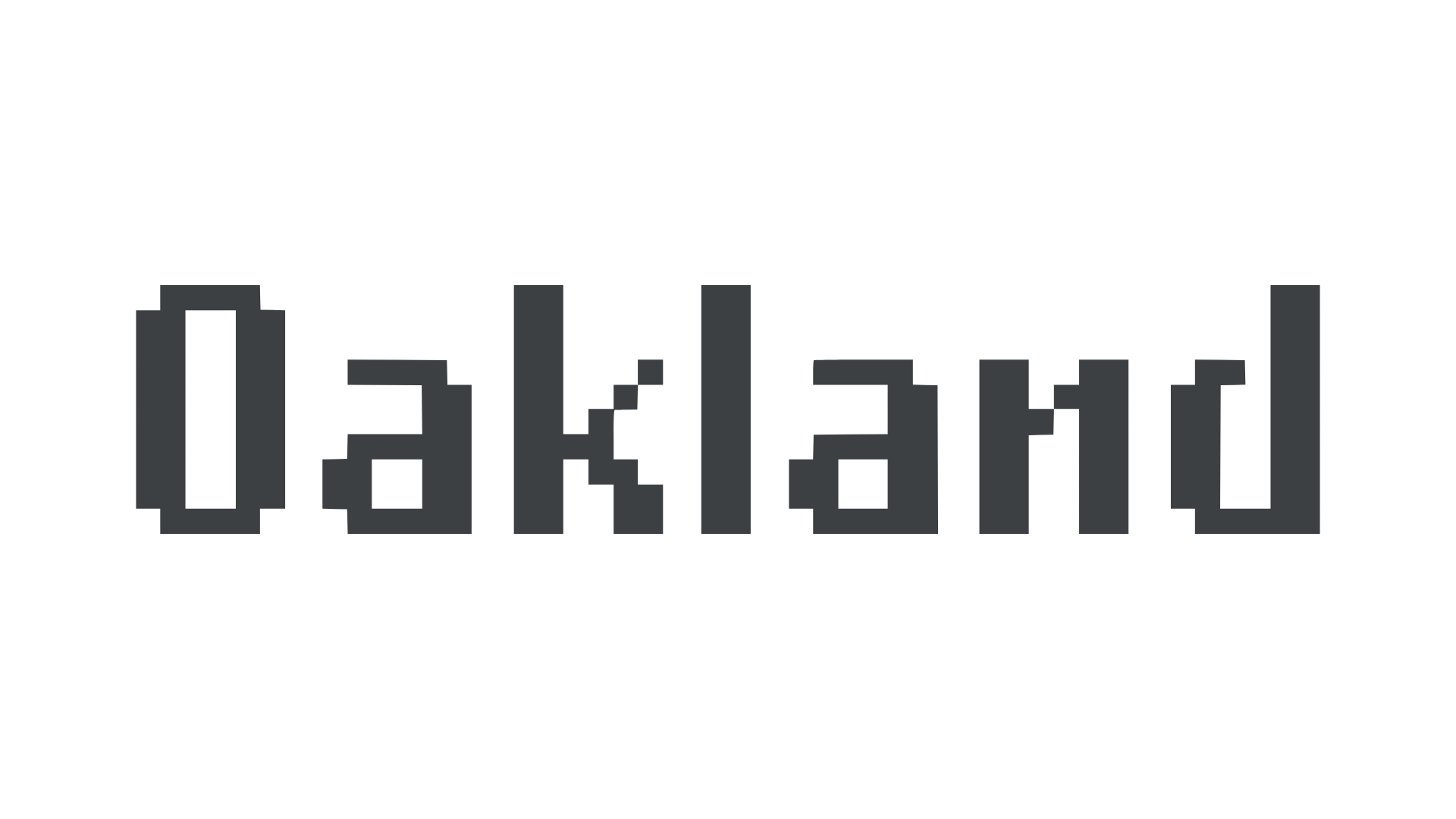
她在1985年用蘋果麥金塔128K設計了Emperor、Oakland和Universal字型系列(2011年以Lo-Res重新發布),後來還創作了多個經典字型的數字復刻版本。
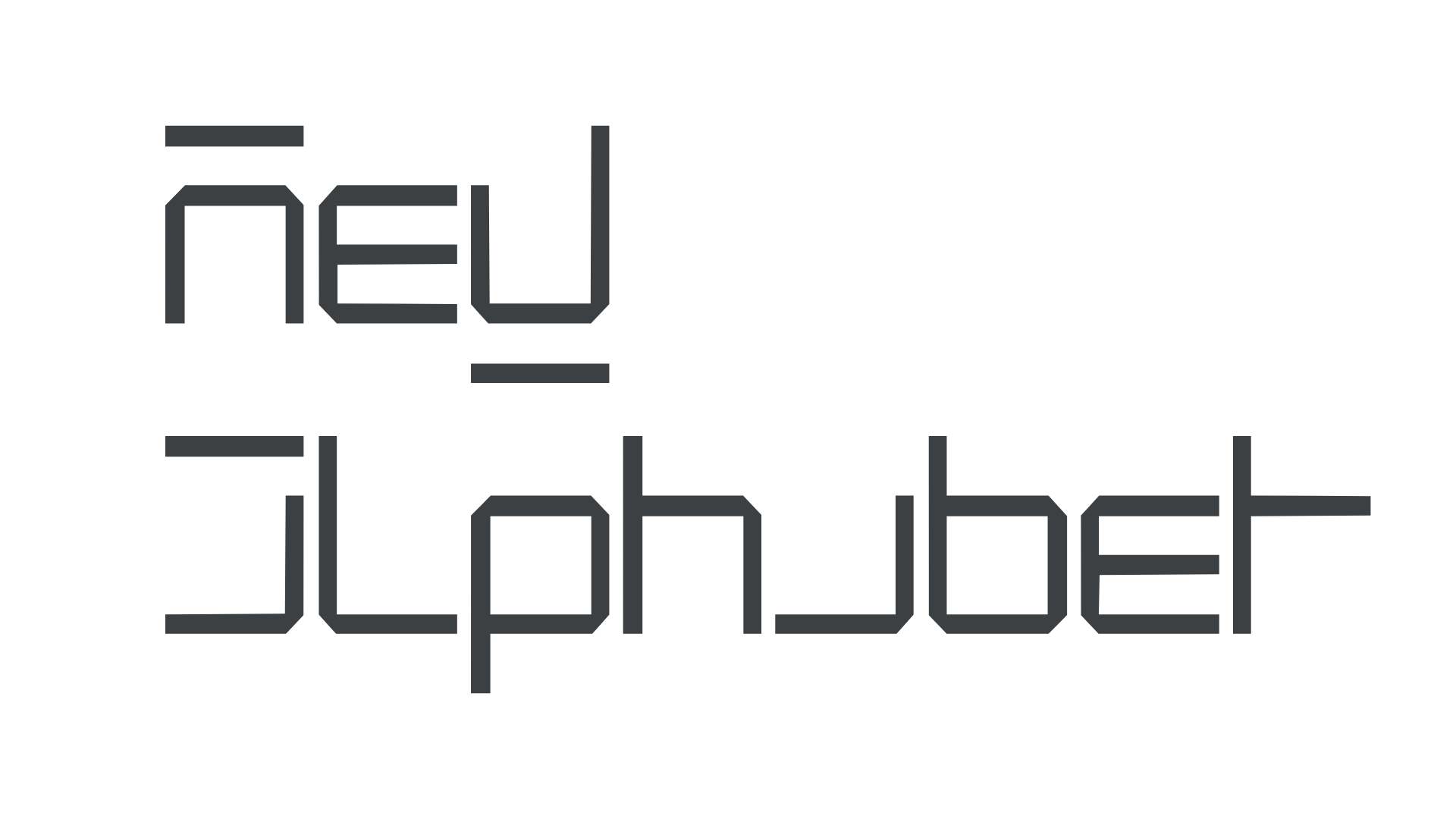
個人電腦和90年代網際網路的普及讓字型設計變得更加平民化。隨著顯示器解析度提高和輪廓字型的出現,新的字型設計層出不窮,從日常手寫到正式書法,從做舊效果到垃圾風格都被重新詮釋。19世紀的彩色字型也以圖層字型的形式重現,近期更發展出可嵌入點陣圖和向量紋理的彩色字型。可變字型技術的發展讓單個字型檔案可以透過粗細、傾斜和寬度等軸心控制多個變體,在印刷和網頁中得到廣泛應用。